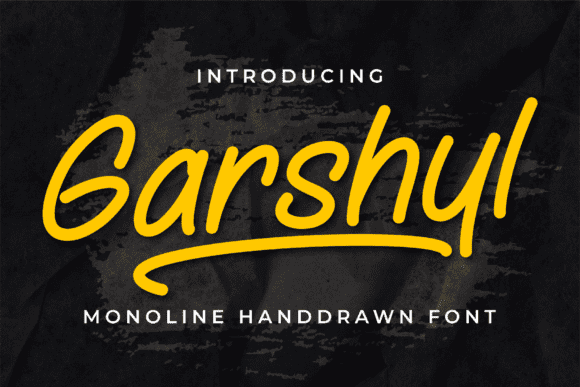
Название: Garshyl Font (2022)
Garshyl - это волшебный шрифт, созданный с особым вкусом и универсальностью.
Ищите ли вы шрифты для Instagram или каллиграфические шрифты для проектов DIY, этот шрифт превратит любую творческую идею в настоящее произведение искусства!
Название: Garshyl Font (2022)
Garshyl - это волшебный шрифт, созданный с особым вкусом и универсальностью.
Ищите ли вы шрифты для Instagram или каллиграфические шрифты для проектов DIY, этот шрифт превратит любую творческую идею в настоящее произведение искусства!